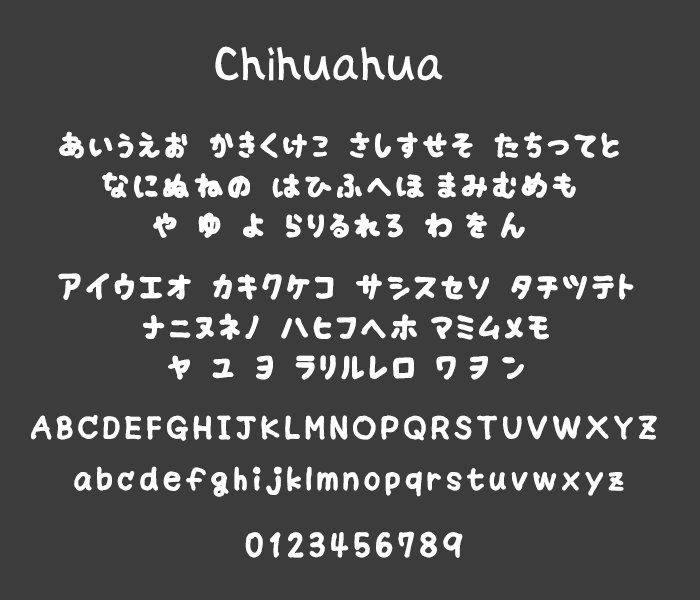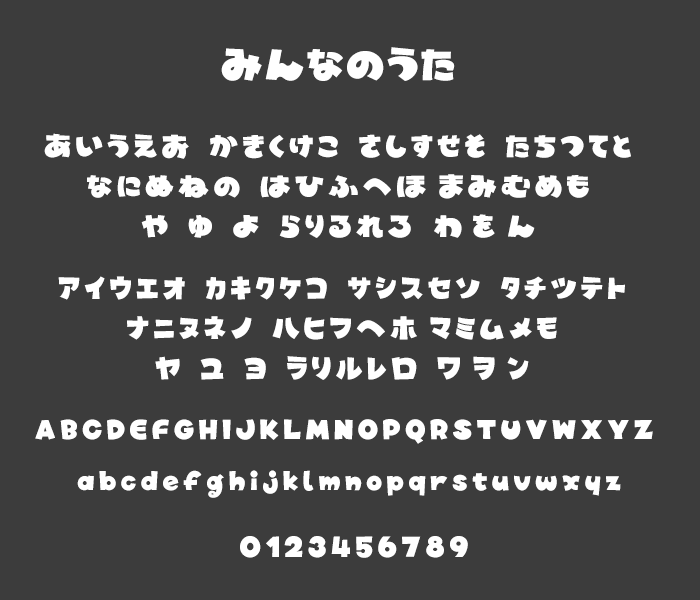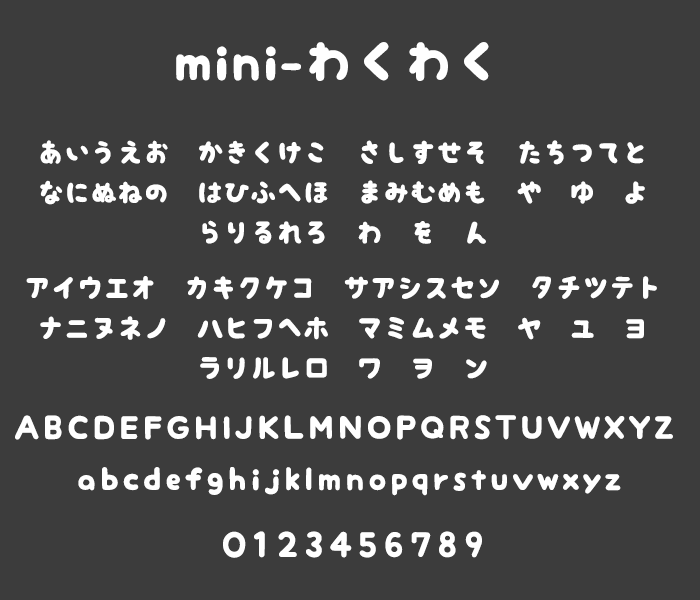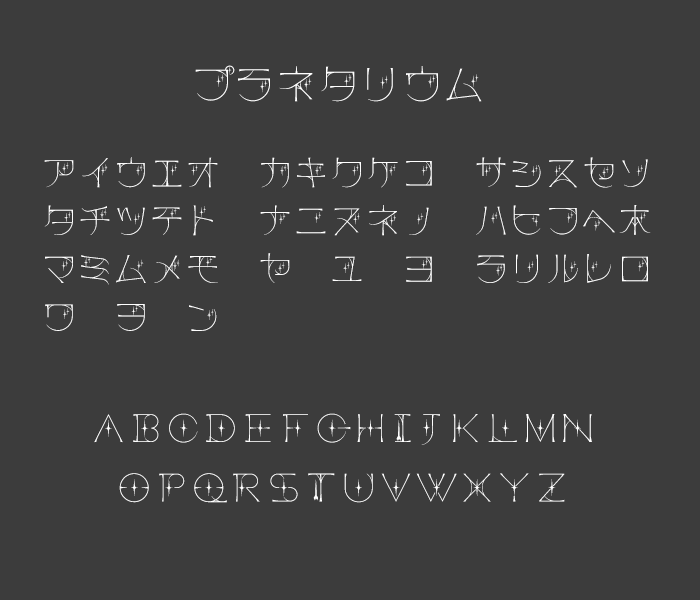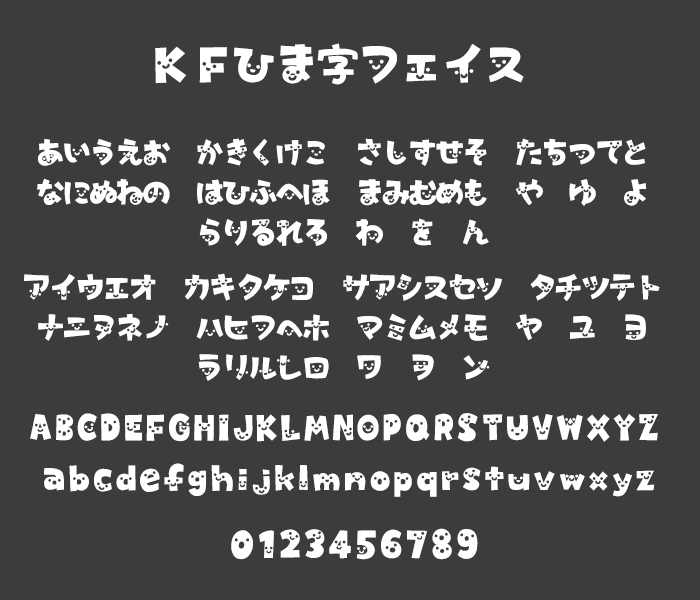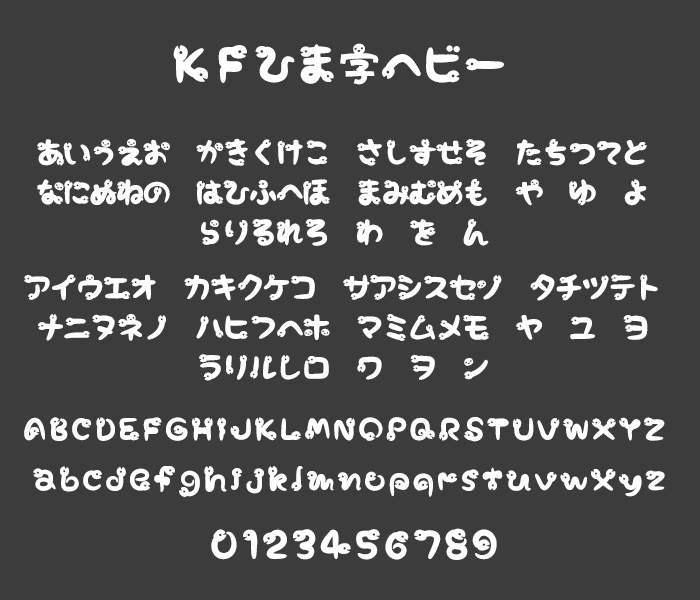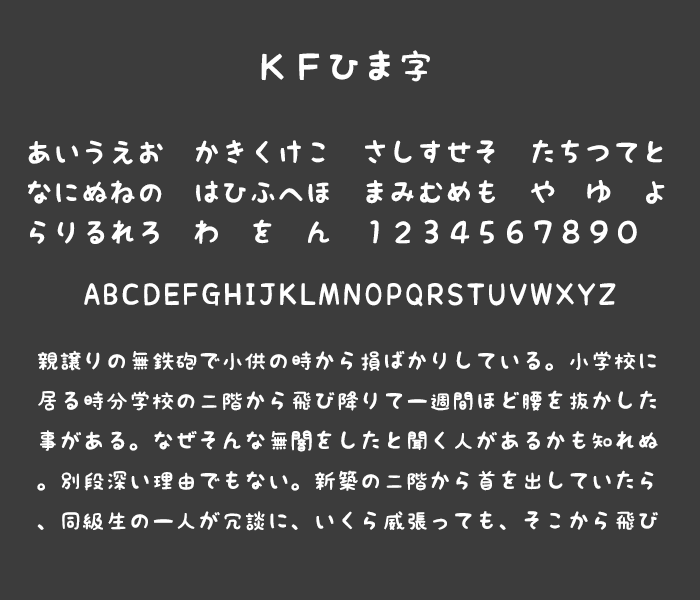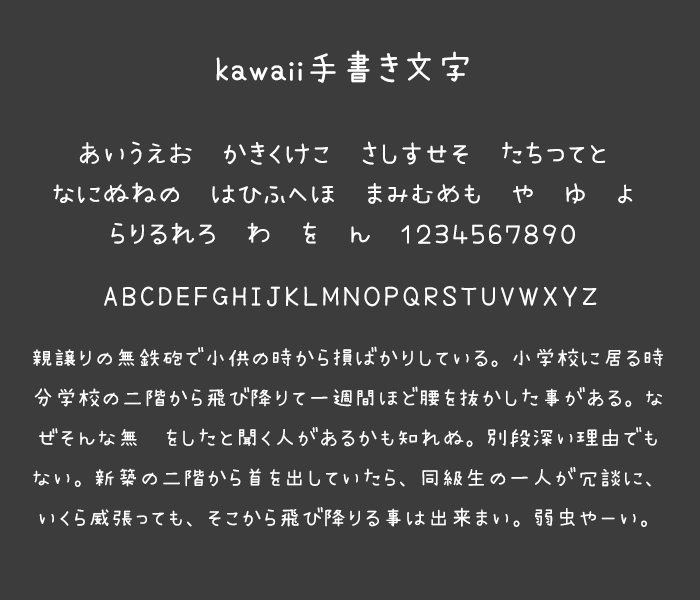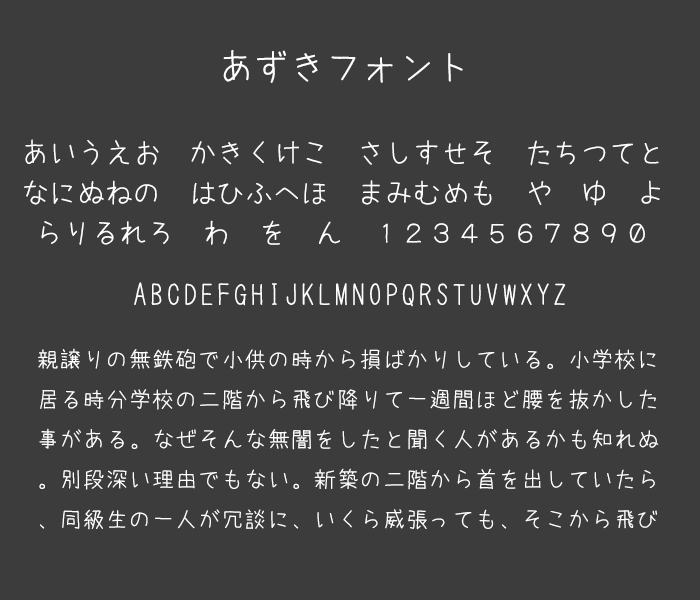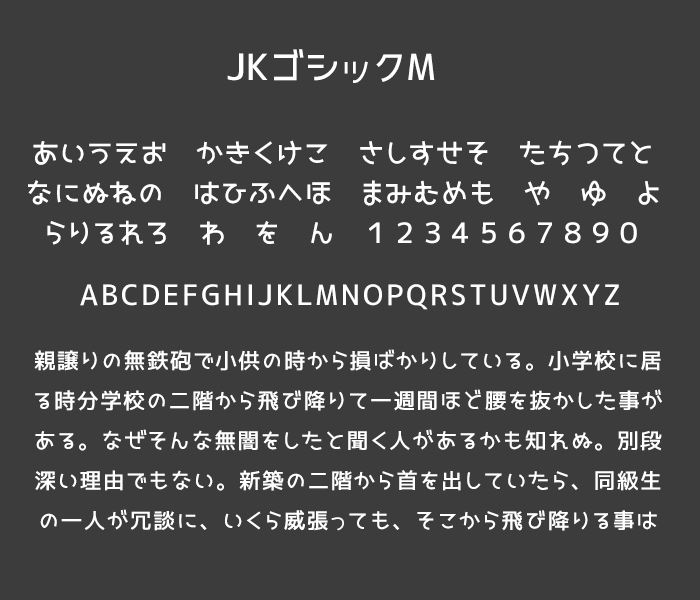
無料で使える日本語・英語のかわいいフリーフォント20選
美容や雑貨など女性をターゲットとしたサイトや印刷物のデザインをする時にかわいい・おしゃれ系のフォントを使用すると雰囲気も大分華やぎます。またベビー・キッズなどの柔らかいデザインをする時にも役に立つでしょう。今回は女子が好みそうなかわいい系日本語・英語フォントを厳選して紹介します。
かわいい日本語フォント
April Fool
手書き文字からベジェを引いて作られたエレメント無しの手書き風フォント
Chihuahua
チワワのように?可愛らしい丸みのある手描き風フォント
みんなのうた
NHKのテレビ番組「みんなのうた」の世界観で、楽しくてレトロな感じの丸みのあるカワイイフォント
mini-わくわく
大人から子どもまで楽しめる、ちょっと手書き風のかわいいフォント
プラネタリウム
夜空に映えるカタカナ、英字フォントです。カタカナには星が2コ、英字には1コ輝いてます。
KFひま字フェイス
文字にかわいい顔が描かれたフォント
KFひま字ヘビー
ニョロっとヘビが文字になってるかわいいフォント
KFひま字
手紙を書いたり、お名前シールを作ったり、ほのぼの手書きタッチなフォント
kawaii手書き文字
ちょっぴりクセのある可愛い手書きペン字フォント
あずきフォント
マジメすぎず、可愛すぎない手書き風のフォント
JKゴシックM
平仮名・片仮名が女子高生風(?)な可愛いフォントの線を太くしたタイプ
かわいい欧文(英語)フォント
HENNY PENNY
おとぎ話のキャラクターHenny Pennyに敬意を表して名付けた遊び心のあるフォント
SPICY RICE
サイケっぽい丸みのあるかわいいフォント
SNIGLET
バルーンで文字を模ったような丸みのあるフォント
Little Cutie
美しいブラシで書いた文字のようなキュートなフォント
Kinkie
ハートを文字に組み合わせたラブリーなフォント
Gochi Hand
女の子が書いたような丸みのある手書き風フォント
Glamourgirl
小文字のみの丸みのあるフォント
Alba
ちょっとクセのある丸みを帯びたフォント
Crushed Out Girl